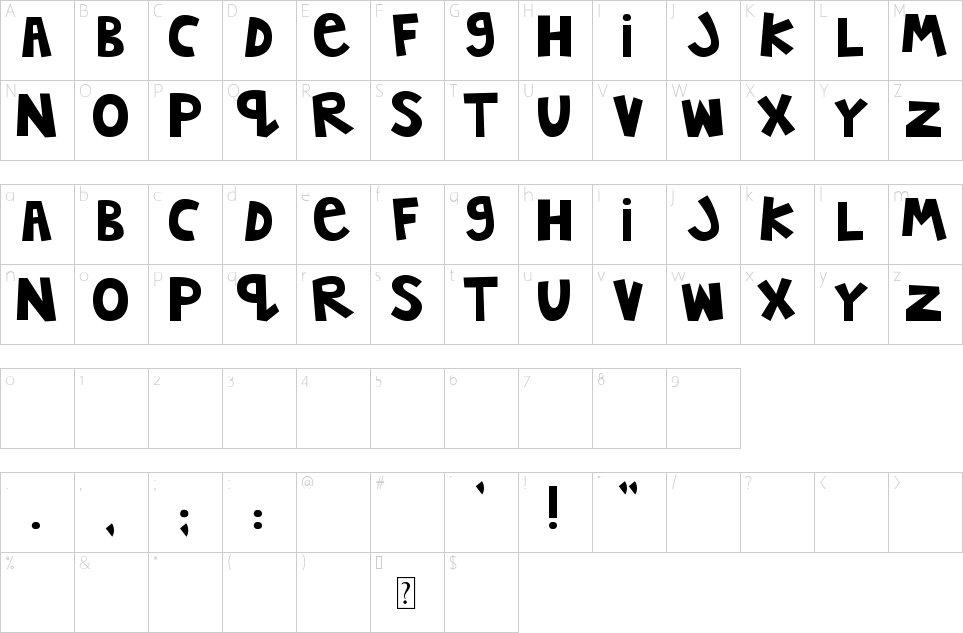
A MTF Jumpin Jack font é uma opção gratuita e divertida para personalizar seu design em qualquer plataforma, seja Windows ou Mac. Desenvolvida pela designer desconhecida Miss Tiina Fonts, essa fonte traz um toque alegre e divertido para qualquer projeto que você esteja trabalhando. Com sua disposição fácil e estilo único, a Jumpin Jack é uma ótima escolha para quem procura uma fonte para adicionar um toque de diversão sem comprometer a legibilidade. Com 21.640 downloads, é evidente que esta fonte está recebendo elogios por seu desempenho incrível. Se você está procurando por uma fonte única e divertida para projetos de design, não poderia haver uma melhor escolha do que a Jumpin Jack. Descarregue agora para experimentar o toque alegre dessa fonte grátis.